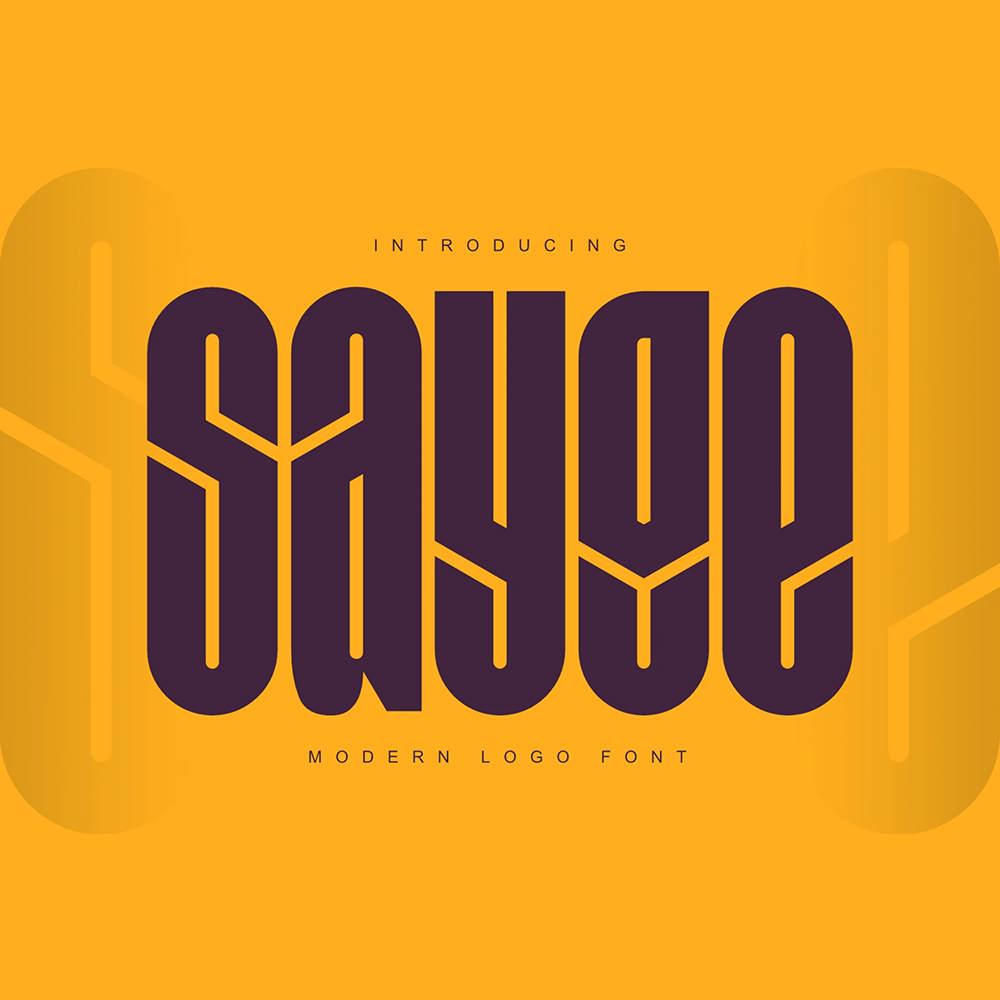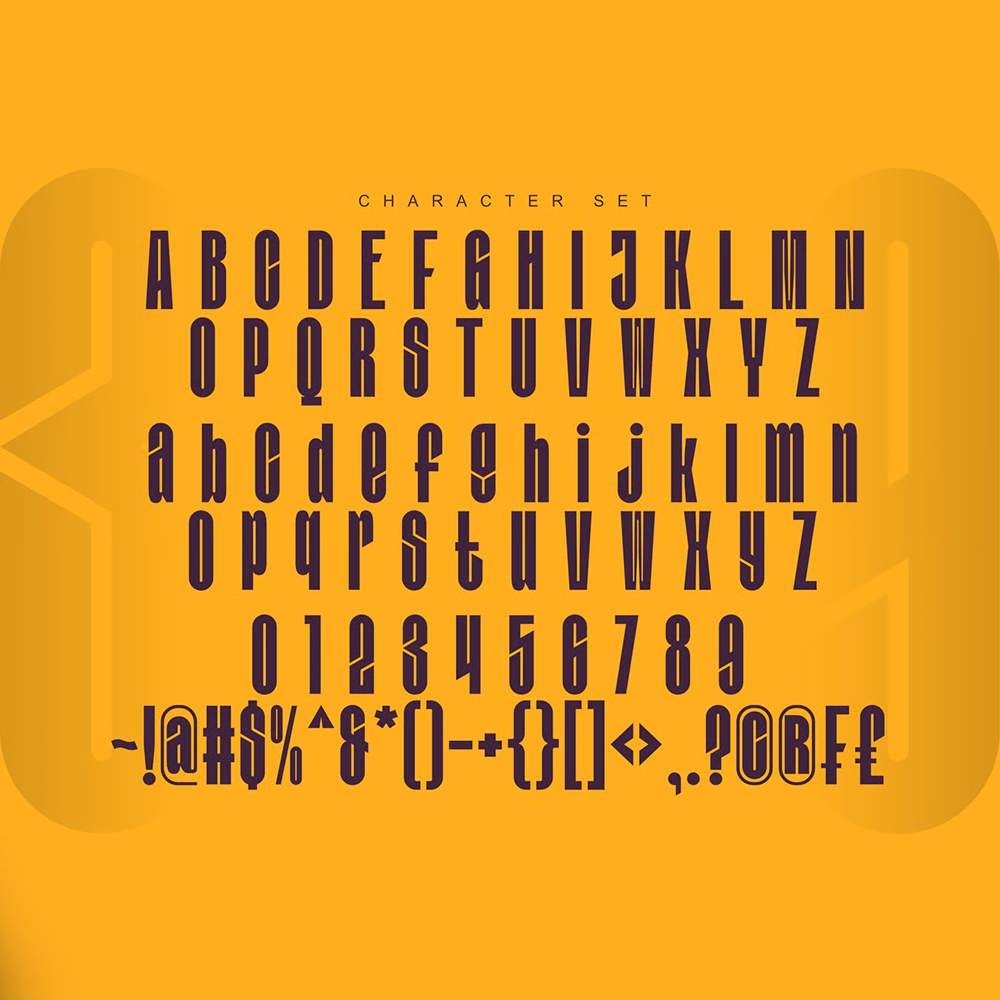
فونت پرمیوم و انگلیسی Sayge Font یک فونت زیبا و نوآورانه است که برای ایجاد جلوهای جسورانه طراحی شده است. اشکال هندسی و خطوط واضح Sayge که…
فونت پرمیوم و انگلیسی Sayge Font یک فونت زیبا و نوآورانه است که برای ایجاد جلوهای جسورانه طراحی شده است. اشکال هندسی و خطوط واضح Sayge که برای برندهای مدرن، طراحی لوگو و پروژههای خلاقانه ایدهآل هستند، اعتماد به نفس و پیچیدگی را القا میکنند. فرم حروف منحصر به فرد آن، زوایای چشمگیر و ساختار متعادل را ترکیب میکند و آن را برای تیترهای تأثیرگذار و کاربردهای متنی زیبا، کاربردی میسازد.